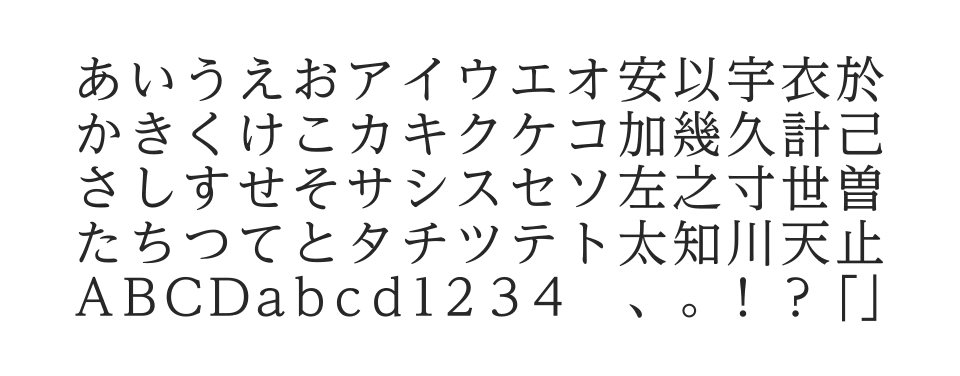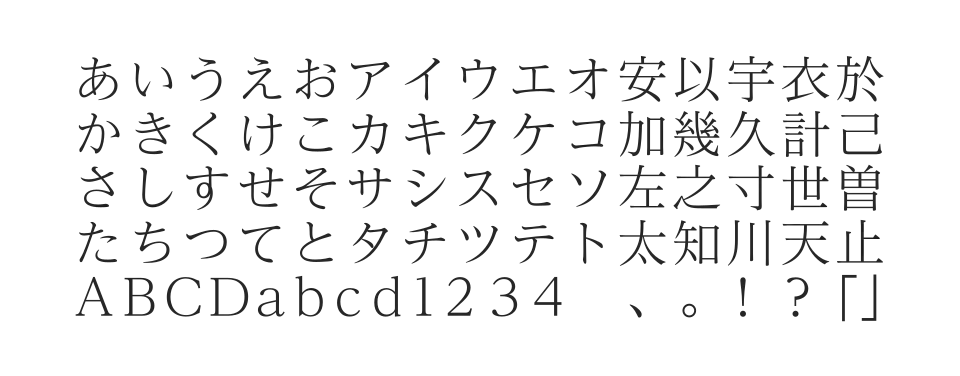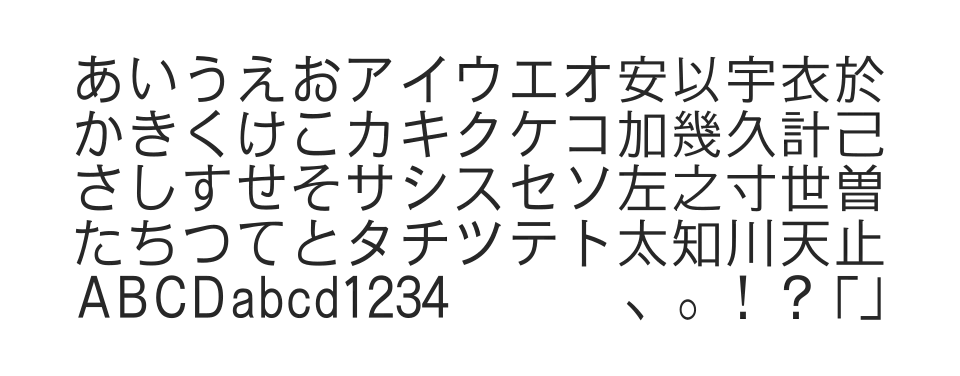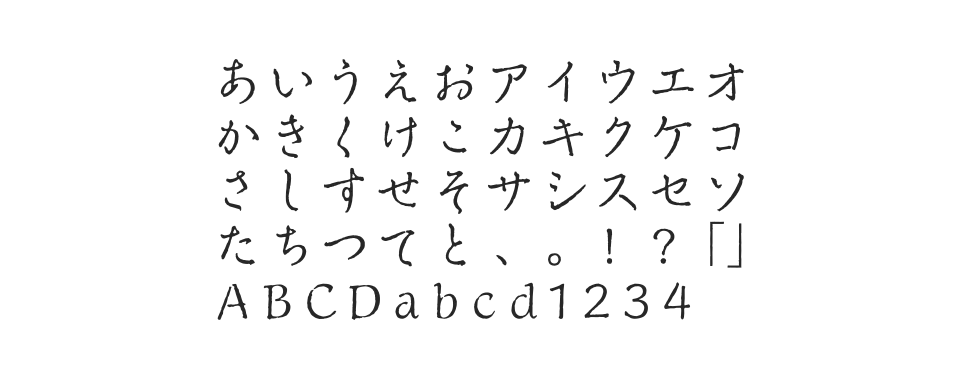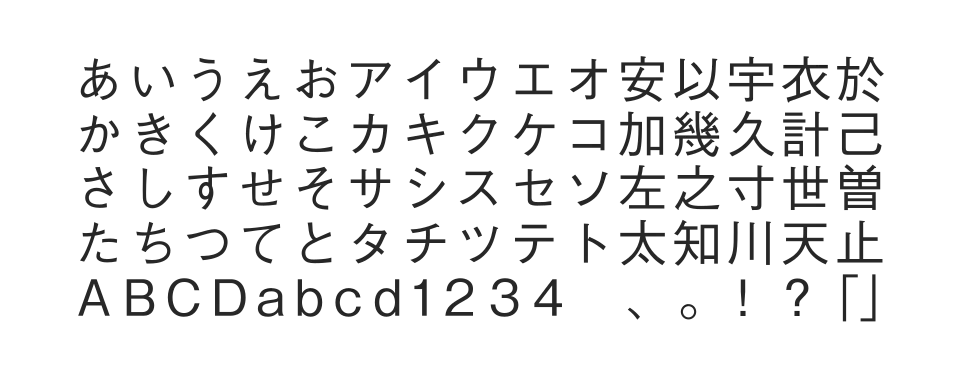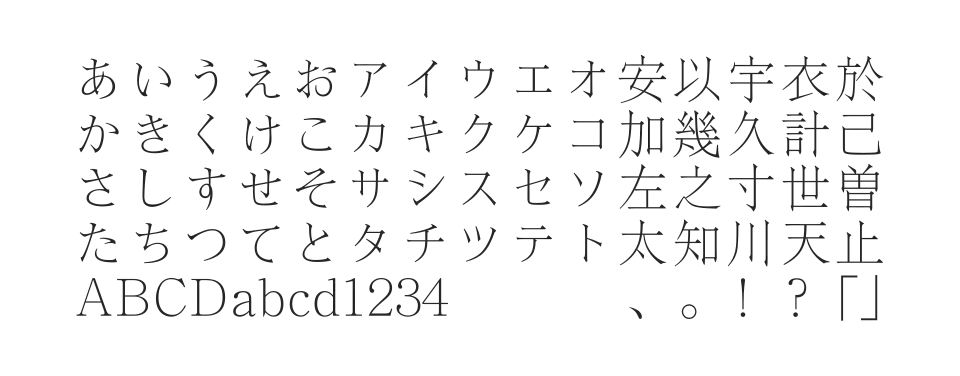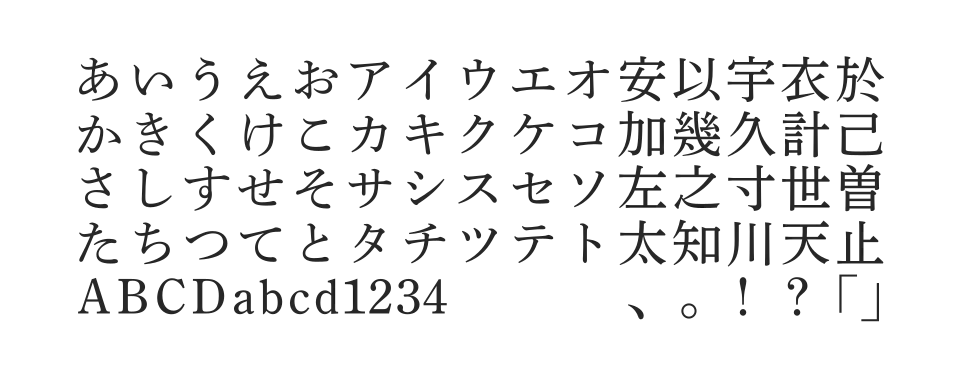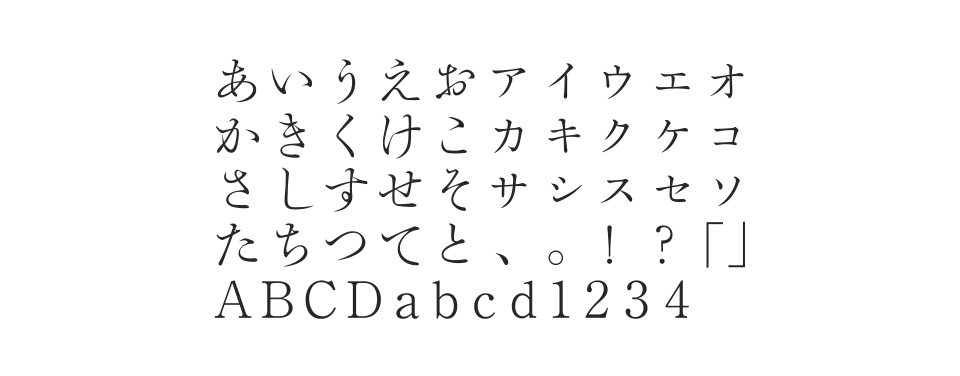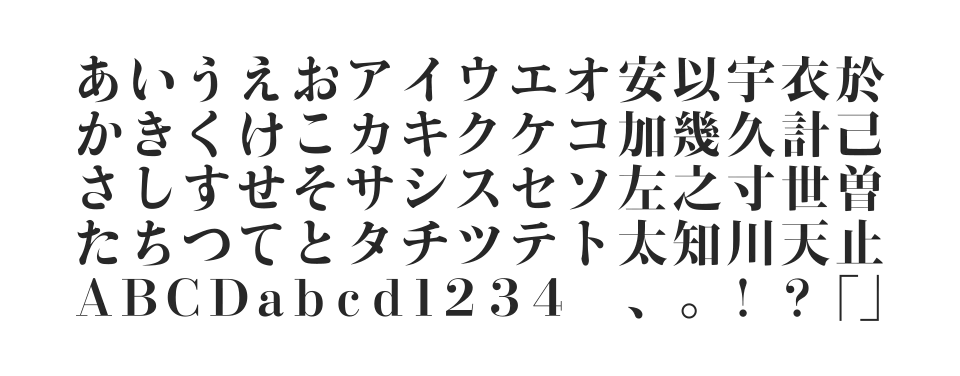
田中一光氏がBodoniに合う日本語書体として開発したオリジナル明朝体。極限まで細い横画と鋭い三角形のウロコが特徴的な、洗練されたモダン明朝です。
大日本印刷が100年以上継承する秀英体シリーズ。伝統的な活字の美しさを現代に蘇らせた、歴史と格式を感じさせる本格的明朝体です。
秀英明朝の横画を太くして視認性を向上させた書体。明朝体の判読性と秀英体の可読性を保ちつつ、スクリーンでも読みやすい革新的な明朝体です。
明朝体と宋朝体の特徴を融合させたオリジナル書体。極限まで引き締まった鋭さと柔らかさを兼ね備え、清冽な表情と上品な雰囲気を持つ個性的な明朝体です。
モリサワを代表するゴシック体の最新仕様版。豊富なウェイトバリエーションと高い可読性を誇り、あらゆる用途に対応する汎用性の高いフォントです。
日本語DTPの幕開けを告げた伝統的なゴシック体。オーソドックスな字形で可読性と安定感に優れ、本文から見出しまで幅広く使用される基本書体です。
手になじんだ万年筆で書き綴ったような趣きと知性を感じさせる書体。にじみの表現で手書きのタッチと紙の質感を演出し、温かみと品格を持つ草書体かなフォント。
新聞印刷に最適化されたゴシック体。高い可読性と判読性を持ち、小さなサイズでも文字がつぶれにくく、新聞や雑誌などの印刷媒体に適した設計のフォント。
シンプルで親しみやすい表情を持つ現代的な明朝体。クセのないニュートラルなデザインで、本文から見出しまで幅広く活用できる高い柔軟性と汎用性を備えたフォント。
黎ミンの横画をやや太くしたバリエーション。小級数使用時や白抜き、写真へのノセなど繊細な書体選びに対応し、優れた可読性を発揮するモダン明朝体。